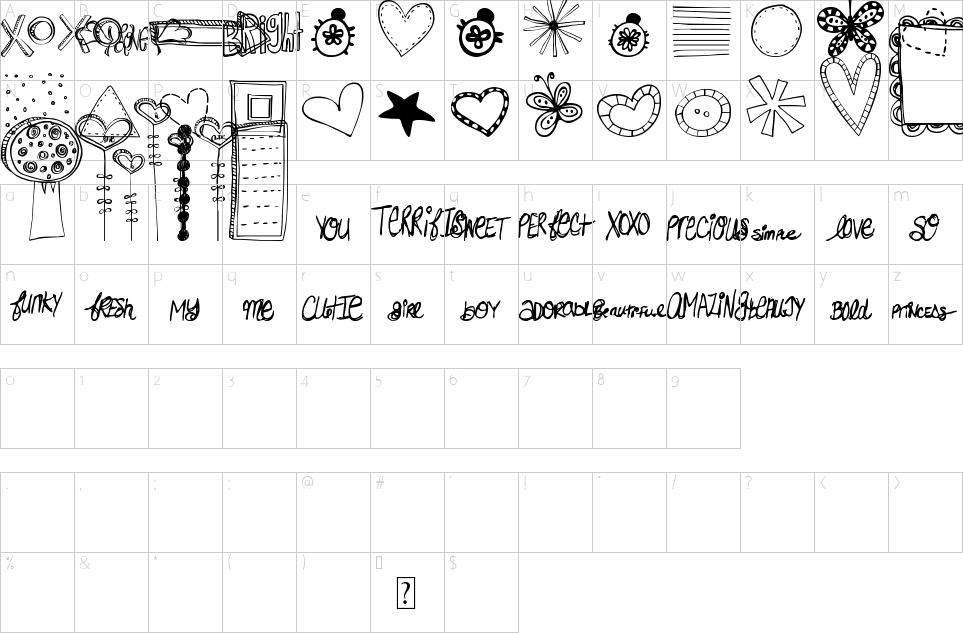
Descubra a charmosa MTF Doodle Whats Font, uma fonte gratuita ideal para quem valoriza a simplicidade e o estilo deslavado do doodle. Desenhada por Miss Tiina Fonts, esta fonte é perfeita para decorar textos de forma criativa e pessoal. Com uma interface fluida e uma aparência minimalista, ela pode tornar suas criações únicas e repletas de personalidade. Esta fonte foi baixada por muitos criadores de conteúdo, designers de web e até mesmo por aqueles que simplesmente adoram a tranquilidade de uma fonte desenhada à mão. MTF Doodle Whats Font é uma excelente escolha para adicionar um toque único e fresco a qualquer projeto. Com apenas alguns cliques, você pode incorporar esta maravilhosa fonte em seus trabalhos. Descubra agora e deixe sua marca com um toque de personalidade e estilo.